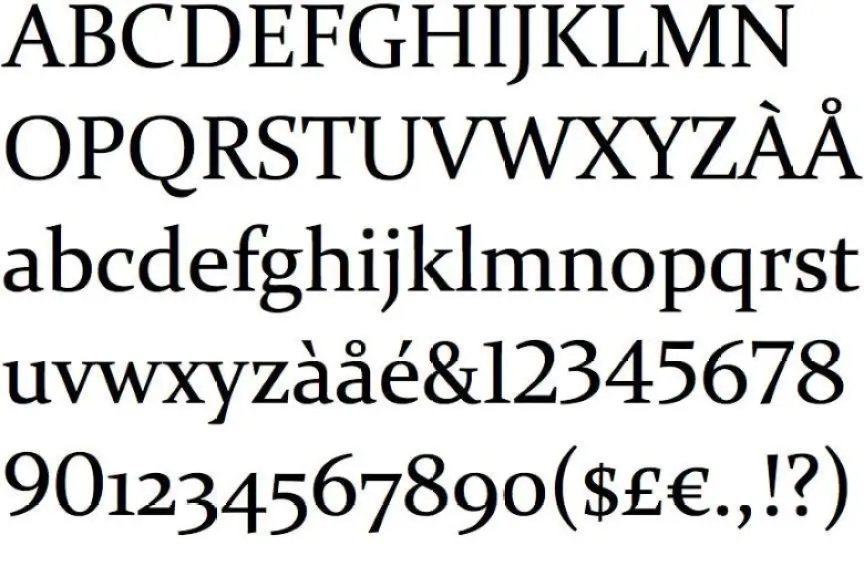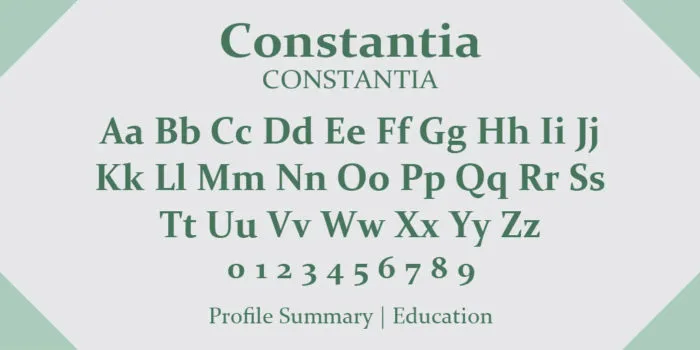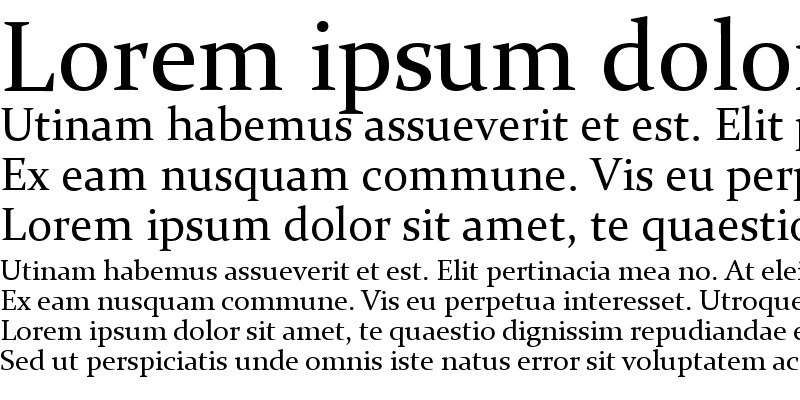
Nhiều designer khi tìm kiếm Constantia font Việt hóa thường gặp lỗi thiếu dấu tiếng Việt, ký tự bị lỗi hiển thị hoặc khoảng cách chữ không đều khi in ấn trên hộp sản phẩm cao cấp. Việc sử dụng phông chữ không chuẩn khiến bộ nhận diện thương hiệu trở nên thiếu chuyên nghiệp, làm giảm giá trị thẩm mỹ của sản phẩm trong mắt đối tác. Xưởng In Viva cung cấp bản tải Constantia font Việt hóa sắc nét gồm đầy đủ định dạng AI, EPS, SVG, PNG, hỗ trợ tối đa cho quy trình in ấn và sản xuất ấn phẩm chuyên nghiệp.
Constantia font là gì và tại sao lại được giới đồ họa ưa chuộng?
Constantia là một phông chữ thuộc dòng Serif hiện đại, gồm cấu trúc chữ vững chãi, các đường chân chữ được bo tròn tinh tế và độ tương phản nét thanh đậm vừa phải, tạo nên một vẻ đẹp cổ điển nhưng vẫn mang hơi thở đương đại. Đây là lựa chọn phổ biến cho các thiết kế nội dung dài, báo cáo doanh nghiệp, bao bì dược phẩm hoặc các dòng sản phẩm yêu cầu tính minh bạch và trang trọng.
Vẻ đẹp của Constantia nằm ở khả năng hiển thị cực tốt cả trên màn hình kỹ thuật số lẫn các bản in truyền thống. Tuy nhiên, rào cản lớn khi sử dụng tại Việt Nam là hệ thống dấu thanh thường bị lỗi hoặc lệch tông so với bộ chữ gốc ở các phiên bản không chính thống. Việc sở hữu phông chữ này giúp các sản phẩm in ấn của doanh nghiệp bạn toát lên vẻ ngoài chỉn chu, chuyên nghiệp và đáng tin cậy.
Lưu ý: Khi bạn sử dụng Constantia font Việt hóa cho các đoạn văn bản dài trên giấy mỹ thuật, hãy chú ý đến khoảng cách dòng (leading) để tận dụng tối đa khả năng đọc tuyệt vời của phông chữ này.
5 Ứng dụng phổ biến của Constantia font trong thiết kế và in ấn
Nhờ phong cách trang trọng và tính ứng dụng cao, Constantia là trợ thủ đắc lực giúp nâng tầm giá trị hình ảnh cho doanh nghiệp thông qua các ấn phẩm đa dạng:
- Thiết kế bao bì dược phẩm và thực phẩm chức năng: Constantia với độ rõ nét cao cực kỳ phù hợp để in thông tin thành phần, công dụng trên hộp giấy. Sự vững chãi của phông chữ mang lại cảm giác an tâm và uy tín cho người tiêu dùng.
- Sản xuất hồ sơ năng lực doanh nghiệp: Những dòng chữ Constantia in trên giấy Couches cán màng mờ tạo vẻ đẹp chuyên nghiệp, giúp đối tác dễ dàng nắm bắt các thông tin chiến lược của tập đoàn.
- In ấn thiệp chúc mừng và Voucher cao cấp: Sử dụng phông chữ này cho các tiêu đề chính giúp ấn phẩm trở nên tinh tế, thể hiện sự trân trọng và chỉn chu của ban tổ chức đối với các khách mời quan trọng.
- Khắc laser sổ tay và bút ký: Logo dùng Constantia font Việt hóa khi khắc trên chất liệu gỗ hoặc kim loại tạo nên độ sâu tinh xảo. Họa tiết chữ mềm mại kết hợp với chất liệu bền bỉ mang đậm phong cách sống hiện đại.
- Trang trí bộ ấm chén gốm sứ tri ân đối tác: Hình ảnh chữ nghệ thuật in nung dùng phông Constantia trên sứ trắng mang lại vẻ đẹp nhã nhặn, bền màu theo thời gian sử dụng.
04 lưu ý kỹ thuật khi sử dụng Constantia font Việt hóa
Để thành phẩm in ấn đạt độ sắc sảo cao, designer và kỹ thuật viên tại xưởng cần chú trọng các yếu tố kỹ thuật sau:
- Kiểm soát độ dày nét chân: Constantia có nét chân bo tròn đặc trưng. Khi in kích thước siêu nhỏ trên tem nhãn, bạn nên kiểm tra xem nét chân có bị mất do mực thấm không đều hay không để điều chỉnh Stroke phù hợp.
- Tối ưu đường Path cho gia công bế nổi: Khi dập nổi logo dùng phông chữ này trên hộp giấy, kỹ thuật viên của In Viva cần làm mượt các điểm neo trong file vector. Việc này giúp khuôn bế thực hiện chính xác, tránh hiện tượng rách mép giấy mỹ thuật.
- Thiết lập hệ màu CMYK chuẩn: Để màu sắc phông chữ sau khi in trung thực với bản thiết kế, bạn hãy luôn làm việc trên hệ màu CMYK thay vì RGB để tránh tình trạng lệch tông màu thực tế.
- Convert font trước khi gửi xưởng sản xuất: Luôn thực hiện lệnh “Create Outlines” cho toàn bộ nội dung chữ trước khi gửi file sang máy in công nghiệp. Bước này giúp tránh hoàn toàn lỗi nhảy font hoặc mất ký tự.